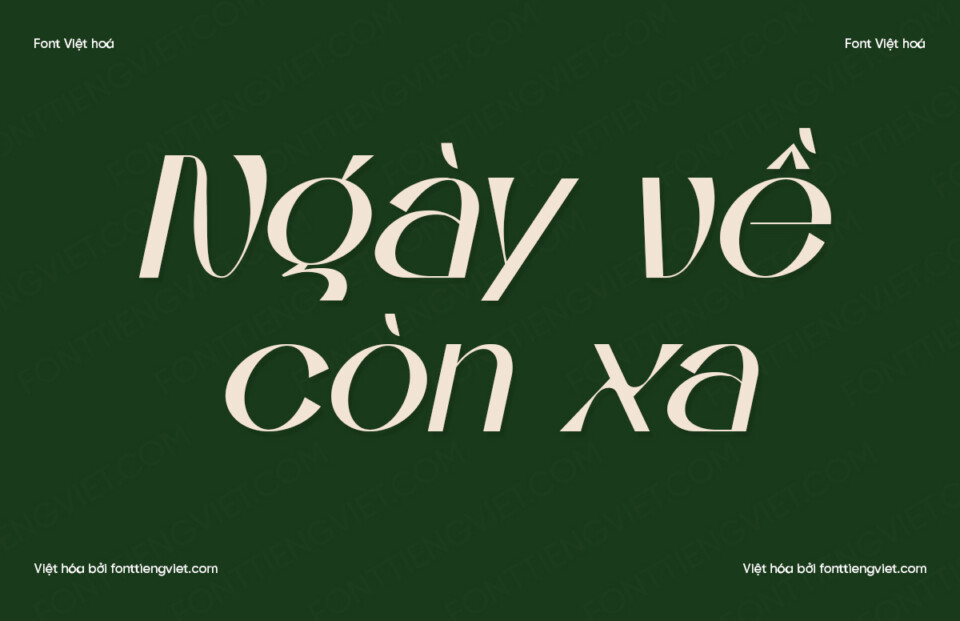
Font Việt hóa 1FTV VIP Amoria Italic
Tải Bộ Font Việt hóa 1FTV VIP Amoria Italic Đẳng Cấp Cho Thiết Kế
Giới thiệu về Font Việt hóa 1FTV VIP Amoria Italic
Trong thế giới sáng tạo nội dung hiện nay, việc lựa chọn một bộ Font Miễn Phí chất lượng luôn là ưu tiên hàng đầu của các nhà thiết kế. Font Việt hóa 1FTV VIP Amoria Italic nổi lên như một giải pháp hoàn hảo dành cho những ai đang tìm kiếm sự kết hợp giữa nét thanh lịch cổ điển và hơi thở hiện đại. Đây là phiên bản được tinh chỉnh kỹ lưỡng về dấu tiếng Việt, giúp người dùng tại Việt Nam có thể sử dụng mượt mà trong các phần mềm đồ họa phổ biến mà không lo lỗi hiển thị. Với đặc tính nghiêng (Italic) đầy nghệ thuật, bộ font này mang lại cảm giác chuyển động nhẹ nhàng, tinh tế và cực kỳ sang trọng cho mọi bản thảo.
Đặc điểm nổi bật của Font Việt hóa 1FTV VIP Amoria Italic
Điểm mạnh nhất của Font Việt hóa 1FTV VIP Amoria Italic chính là những đường nét uốn lượn được thiết kế công phu. Các ký tự không chỉ đơn thuần là nghiêng đi mà còn được tạo hình để tạo ra sự liên kết nhịp nhàng giữa các chữ cái. Điều này đặc biệt quan trọng trong các thiết kế cần sự mềm mại như thiệp mời đám cưới, bìa sách văn học hoặc các dự án thương hiệu thời trang cao cấp. Bộ font này hỗ trợ đầy đủ các ký tự đặc biệt và hệ thống dấu tiếng Việt chuẩn xác, đảm bảo tính thẩm mỹ cao nhất cho người dùng.
Ứng dụng của Font Việt hóa 1FTV VIP Amoria Italic trong thực tế
Khả năng ứng dụng của Font Việt hóa 1FTV VIP Amoria Italic cực kỳ đa dạng, từ lĩnh vực in ấn truyền thống đến thiết kế kỹ thuật số hiện đại. Sự linh hoạt này giúp nó trở thành một công cụ đắc lực cho cộng đồng designer Việt Nam.
Thiết kế nhận diện thương hiệu và Logo
Với vẻ ngoài cao cấp, font chữ này thường được các nhãn hàng lựa chọn để làm biểu tượng hoặc slogan. Khi sử dụng Font Việt hóa 1FTV VIP Amoria Italic cho logo, thương hiệu sẽ toát lên vẻ chuyên nghiệp và uy tín. Những nét mảnh và dày đan xen tạo nên một cấu trúc thị giác vững chãi nhưng không kém phần thanh thoát.
Thiết kế ấn phẩm truyền thông mạng xã hội
Trong thời đại hình ảnh lên ngôi, các bài đăng trên Facebook, Instagram hay TikTok luôn cần những font chữ bắt mắt để thu hút sự chú ý. Font Việt hóa 1FTV VIP Amoria Italic giúp các trích dẫn (quotes) hay tiêu đề video trở nên nổi bật hơn. Nó tạo ra một không gian nghệ thuật riêng biệt, giúp nội dung của bạn không bị hòa lẫn giữa hàng ngàn thông tin khác trên bảng tin của người dùng.
Kết luận về bộ Font Việt hóa 1FTV VIP Amoria Italic